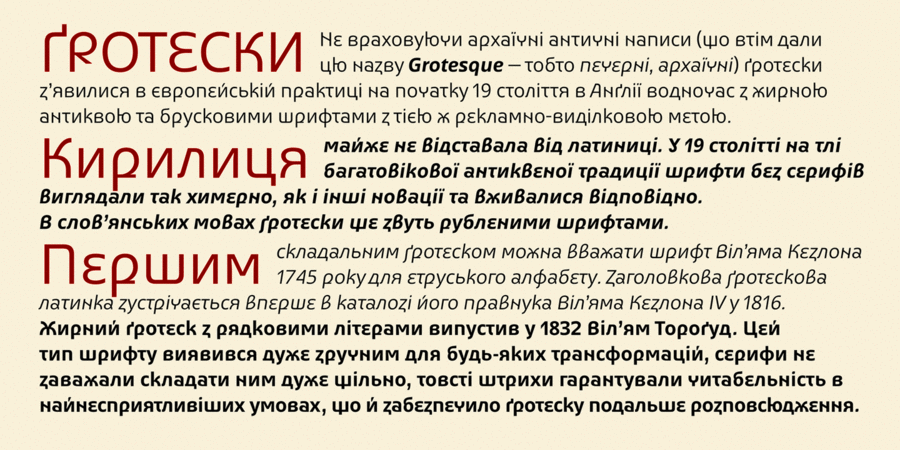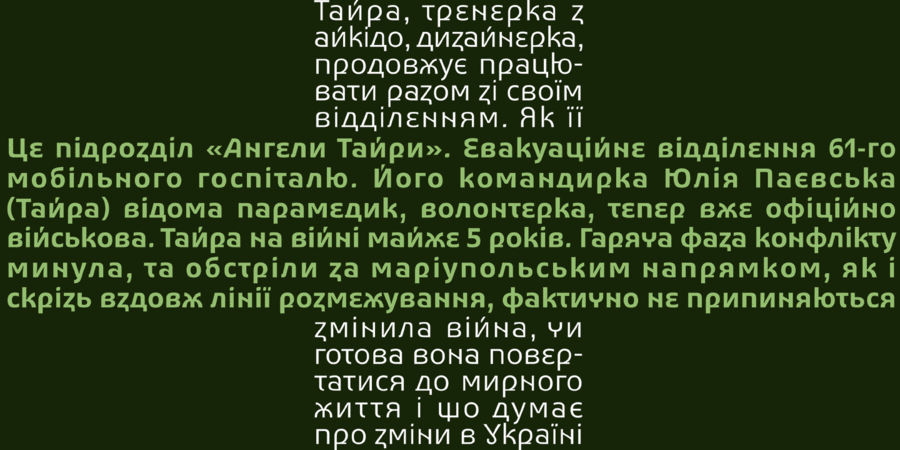
Український ґротеск – простий, демократичний, універсальний шрифт, побудований за принципами, що їх викладає Василь Якович Чебаник – автор «Графіки Української Мови». UkrSans підтримує розширену європейську латинку та сучасну слов’янську кирилицю. Шрифт розробив Віктор Харик у 2019 році.
Асоціації з сімейством шрифтів UkrSansОсобистість і характер гарнітури:
приємний, комфортний, зрозумілий, доброзичливий, ввічливий, акуратний, неквапливий, помірний, органічний, довірчий, оригінальний, самобутній, цікавий, пластичний, гнучкий, гладенький, якісний, динамічний, чистий, ясний, доступний, міський, формальний, Простий, привітний, живий, чесний, здоровий, позитивний, теплий, серйозний, впевнений, стійкий, переконливий, твердий, солідний